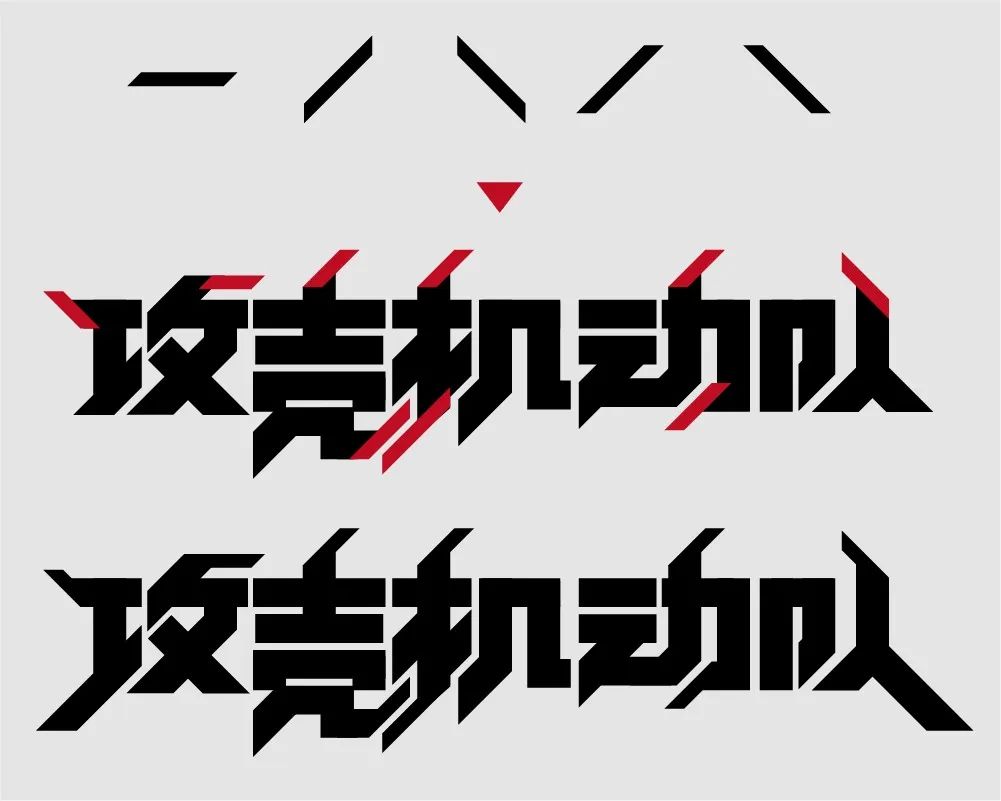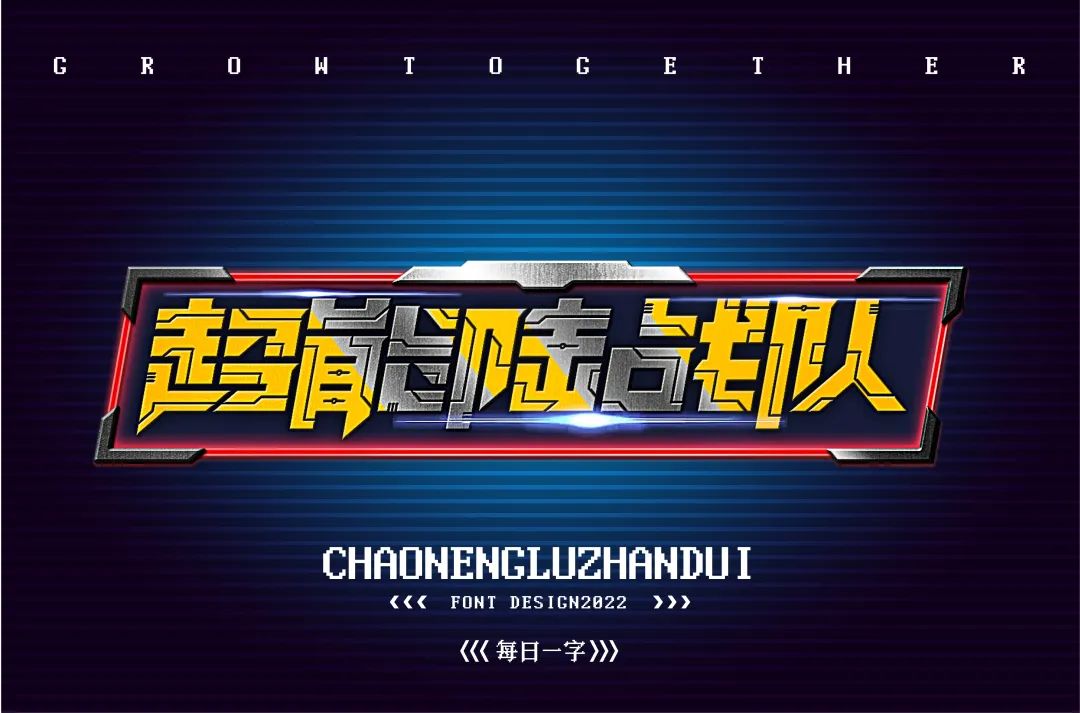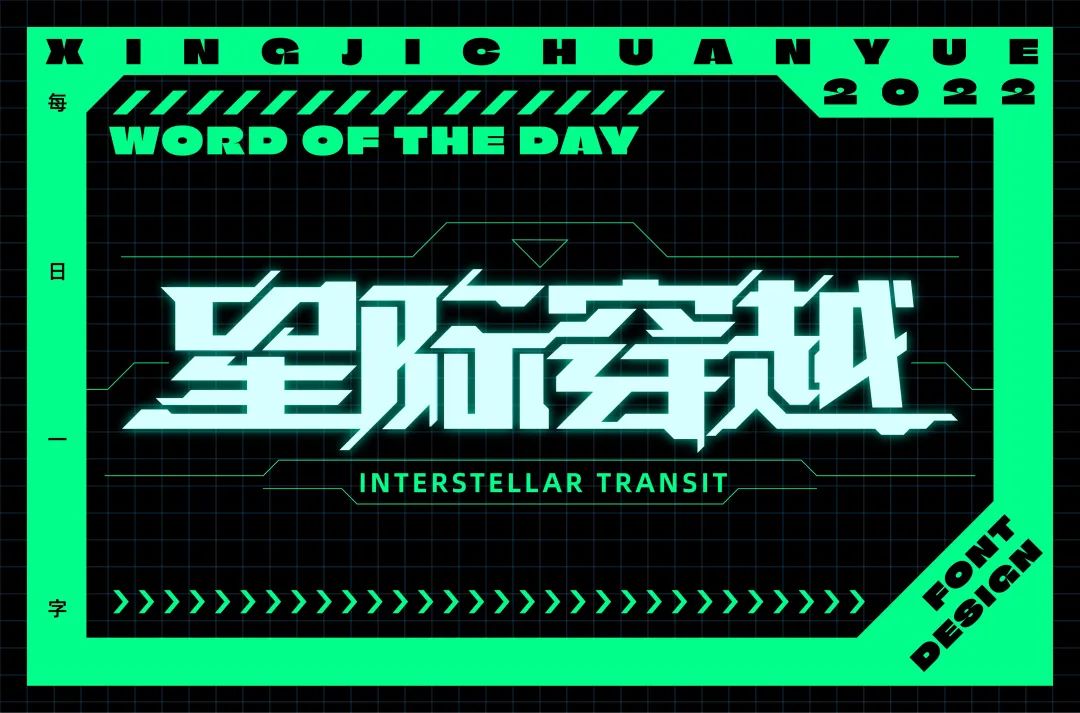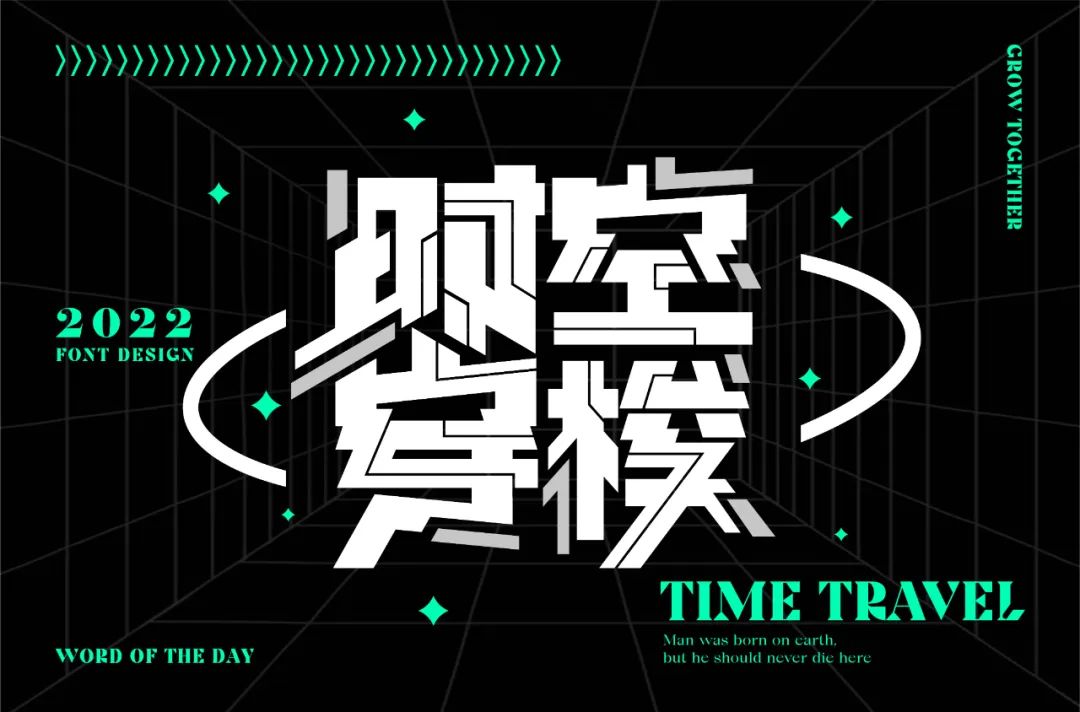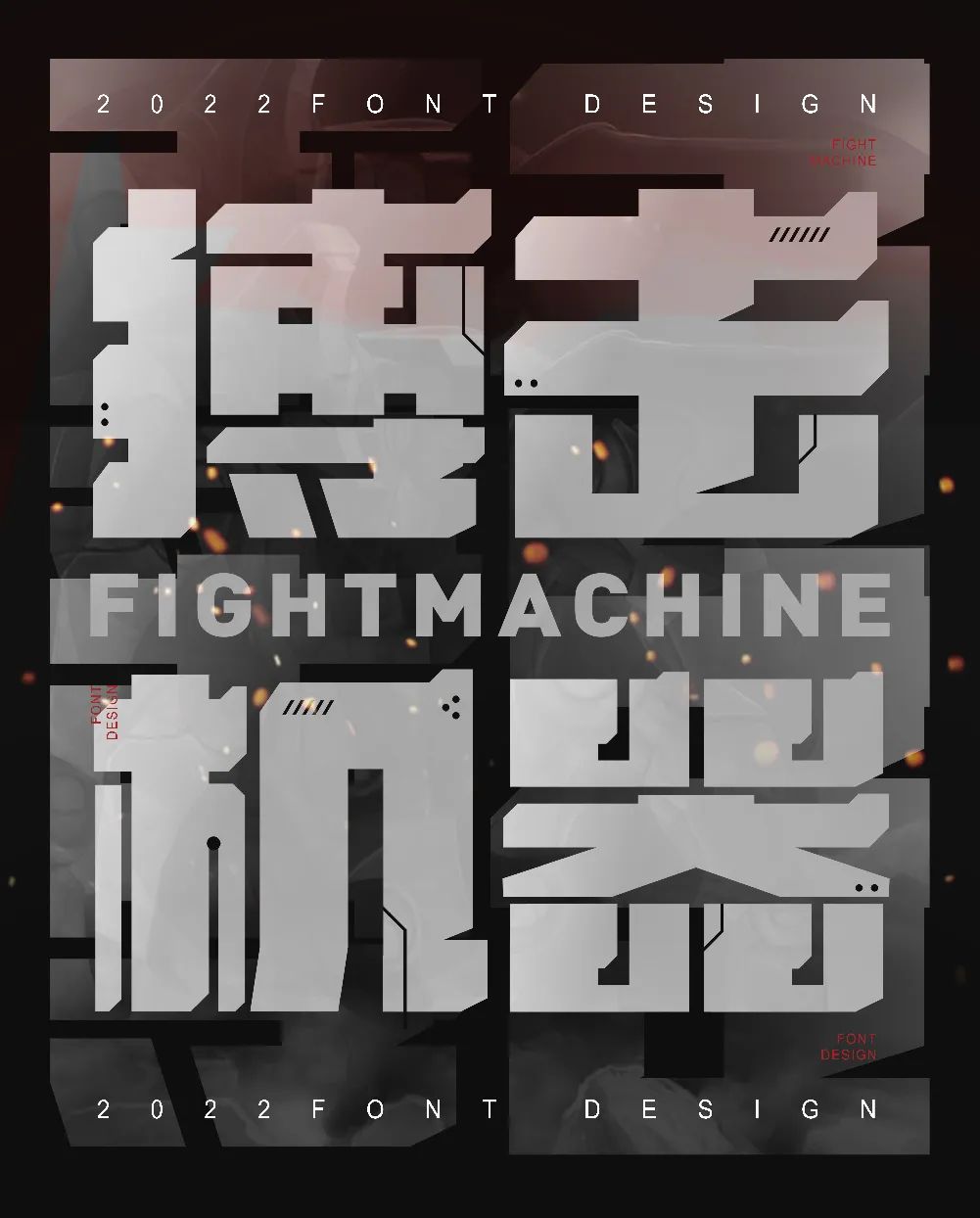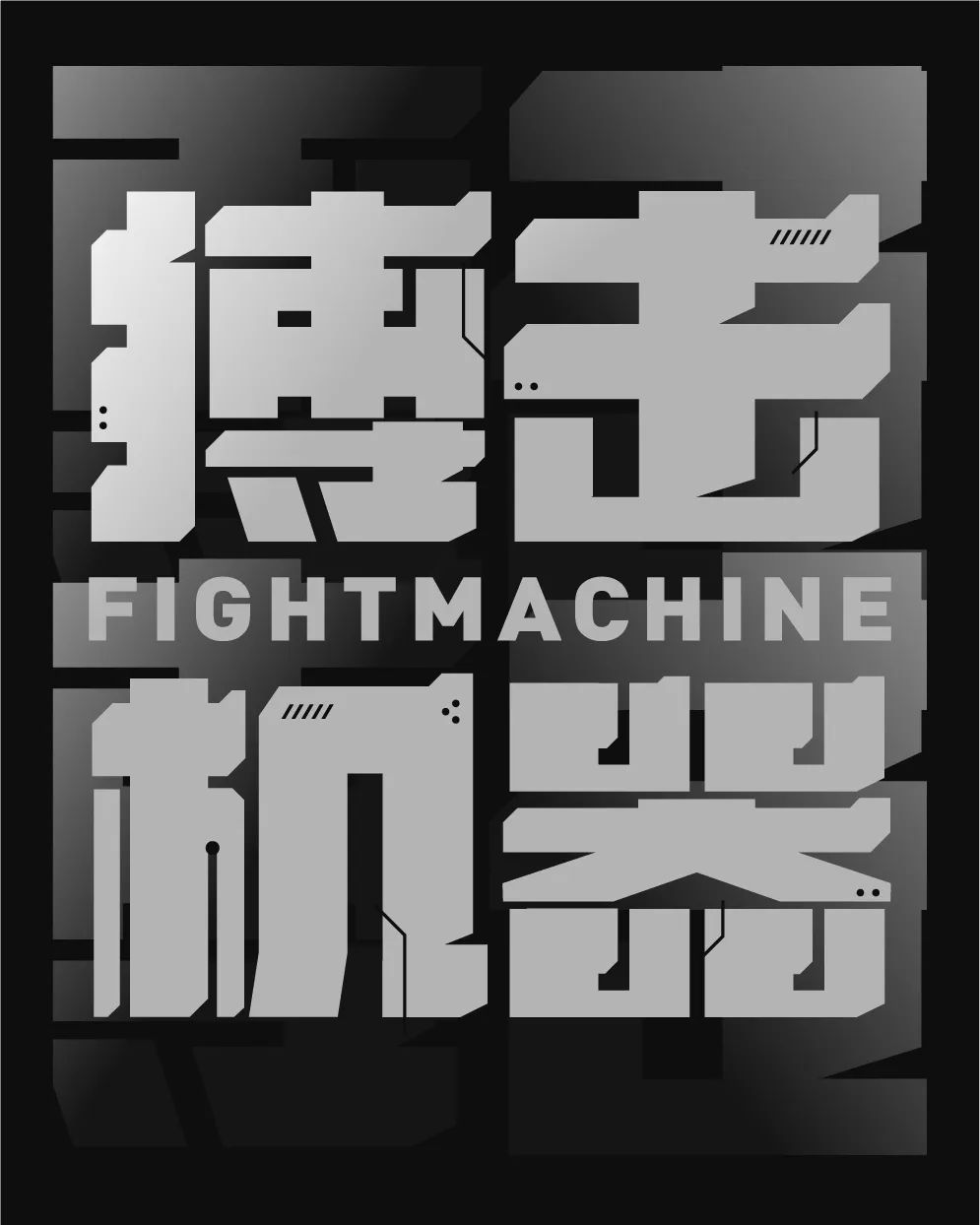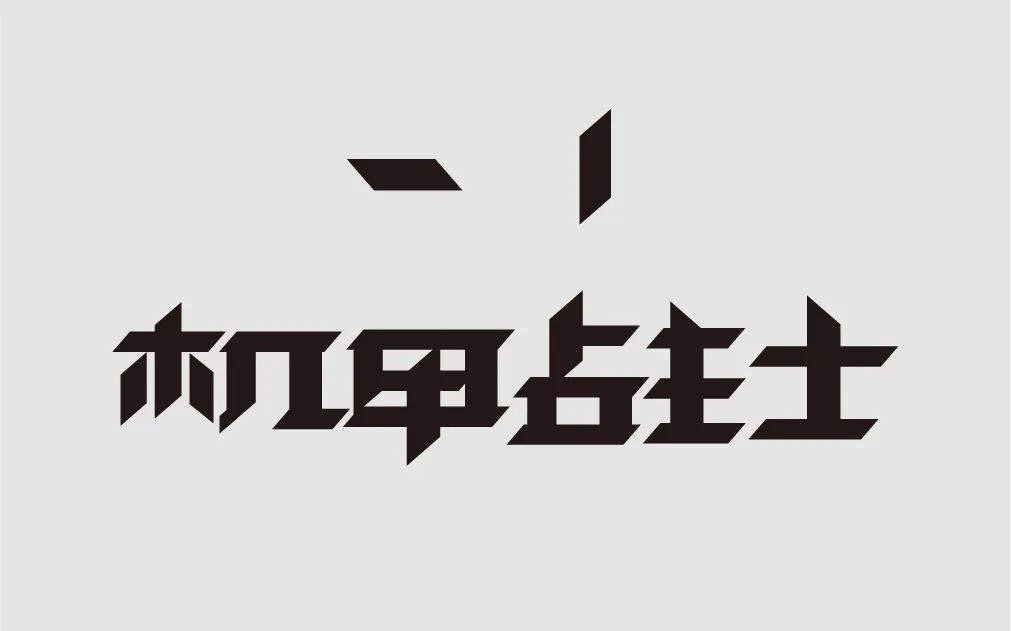
4种方式的机甲风字体教程,超炫酷!
机甲风的字体设计风格,这几年是比较火爆的,无论是字体帮的投稿作品,还是其他平台的字体作品,这类风格的出现频率很高,好多设计师都在做。
原因嘛,当然很简单:这类字够酷,够靓,够吸睛!
这类字体的特点,我们可以用几个关键词概况一下:
科技感、未来感、硬朗风、炫酷风。
今天,我们就分4种方式,共8个案例,将这类风格一网打尽!
看完这篇教程,轻松做出带感的机甲风字体!
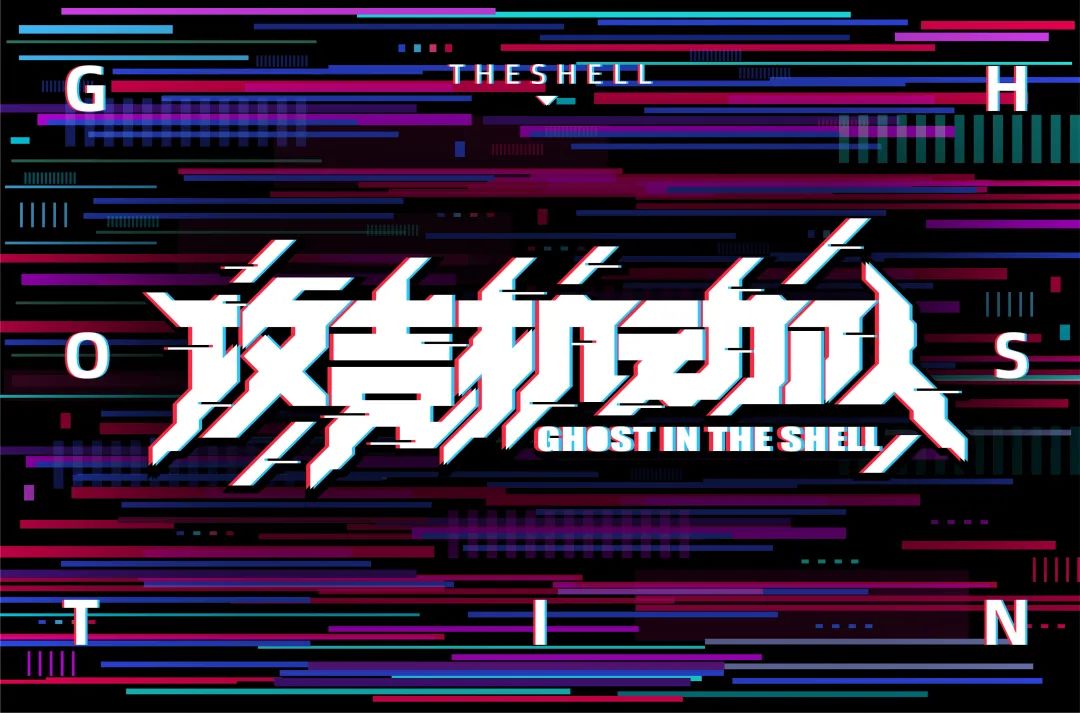
第一步:用矩形工具,画出几个基础笔画,斜笔画保持45°,动作要快,姿势要帅:
第三步:结构搭建完成后,对字体的斜笔,进行切平处理:
第五步:选中一个斜笔画,按住alt键,复制到笔画的边缘,再选中这两个笔画,在路径查找器中,点击相减,对其他笔画,也进行相同的操作:
第六步:继续给字体添加装饰,装饰中的斜线,都需要保持45°:
方式1-案例B
先看最终效果
第三步:先画几个几何图形,将几何图形作为装饰,复制到笔画的边缘和末端,还有拐角的位置:
第四步:在字体周围,以对称的姿势,画出一些带有科技感的线条,然后加入英文:
最后简单排版,搞定!
方式2-案例A
先看最终效果
第一步:使用矩形工具,搭建出字体的基础结构:
第二步:将字体的所有横笔画和竖笔画,间距统一,使字体结构更有个性,这样看起来也更舒爽一些:
第三步:选择钢笔工具,使用白色描边,在笔画内部,添加类似线路板的装饰,在添加的过程中,发现“战队”两个字,整体偏小,这里对这两个字,进行适当的调整:
第四步:全选字体,点击对象→扩展,再次全选字体,在路径查找器中,点击分割,然后选择魔棒工具,填充颜色设置为0,点击白色线条,选中白色线条后,将它删除:
第五步:给字体添加一个边框,再倾斜10°就完成了:
加上一个简单的字效,并配上排版,搞定!
方式2-案例B
第一步:使用万能的矩形工具,搭建出字体结构:
第二步:调整四个字的排版,对字体进行连笔和断笔的设计,最后,延长部分笔画,增加设计感,让字体更有冲击力:
第三步:选择钢笔工具,使用白色描边,在笔画内部添加装饰,不知道如何添加的话,可以参考线路板的造型:
第四步:全选字体,点击对象→扩展,再次全选字体,在路径查找器中,点击分割,然后选择魔棒工具,填充颜色调整为0,点击白色线条,选中白色线条后,将它删除:
第五步:把字体笔画边缘的图形,向外移动,让字体有破碎的感觉,然后给字体添加图形装饰:
最后,排个版,完成!
方式3-案例A
还是先看最终完成后的效果
第一步:先在画板中画出四个正方形:
第二步:在正方形旁边,用矩形工具做出基本字形:
然后放大字体,可以看到,重字做的很挤,返字两个斜线笔画伸的很长,这些都是问题:
所以,有错就要改!
下面,我们来看一下修改的前后对比:
此刻,我突然想起了最初的四个正方形,第一步时,我就画出了它们,我并不是没事闲的dan疼,而是……
而是……我另有所图!
接下来的这一步,我就将正方形作为装饰,加入到了字体里边!
作为一个深谋远虑的设计师,我早就看透了世间的一切,提前做出了准备!
第三步:以重字的横线为例。在笔画的右侧,设置45°的倒角设计:
举一反三,给其他字体添加倒角,机甲风的感觉,瞬间就有了!
继续添加矩形线条装饰,并做出一些切割元素:
放大来看一下:
最后简单排个版,完事!
方式3-案例B
先看最终效果
第一步:用矩形工具搭建出字体结构:
第二步:选择性的加粗一些笔画,让字体更厚重一些,体现搏击的力量感:
第三步:给字体添加一些断笔和切角,平衡负空间,增加设计感:
第四步:给字体的边角处,添加一些45度的倒角和衬角。衬角大小,根据每个笔画的空间大小调整,视觉舒适即可:
第五步:添加一些机甲风格的小元素装饰。置于字体最上方,进行切割镂空,这类小元素,非常实用:
给字体更改颜色,然后复制一层字体,添加渐变色,叠于字体下方:
添加年份和英文等文案,进行排版组合,完成!
方式4-案例A
第一步:用矩形工具搭建出字体结构:
第二步:设定45度角度切割笔画,斜笔的倾斜角度也统一为45度。注意字体笔画之间的穿插切割关系:
第三步:给字体添加断笔,并且融入机甲风切割小元素,角度同样为45度:
第四步:突出英字中的其中一笔,给字体整体添加一个倾斜效果,增加一些动感和气势:
第五步:给字体整体合并,添加镂空线条装饰元素,重新配色:
单独复制出一层字体,做出一个暗金色的渐变色,置于字体最上方,向左移动几下,做出一个微立体效果:
放大看一下,是这样滴:
惯例,做一个排版,效果完成!
方式4-案例B
来,先看效果
第一步:设定一个倾斜角度的笔画,草率的搭建出字体结构,找一下感觉。同时,想一下中午饭吃什么:
接下来,稍微正经一点,规范一下四个字的字面大小和结构比例:
接下来,又该加装饰了,又该化妆了!
倾斜的四边形线条,多复制一些,安放在笔画的边边角角上:
然后,笔画还是比较单调乏味,少了一丝丝情趣,现在,加点料进去!
啪的一声,加完了:
再给字体添加拼音和装饰:
老习惯了,简单做个排版,完成啦!